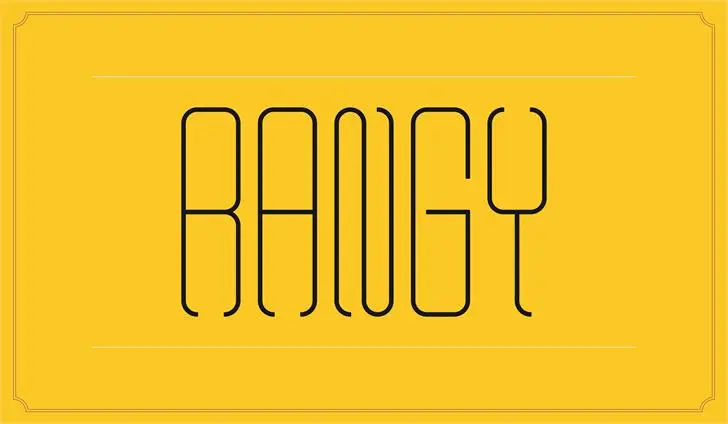
Rangy Font – Fonte Grátis
Rangy Font
A fonte Rangy é uma experimentada tipografia livre para uso comercial e pessoal projetada especificamente para títulos de revistas de moda e produtos cosméticos. Inspirada nos papéis clipados, esta tipografia foi desenvolvida seguindo as medidas da proporção dourada. Além disso, Rangy destaca-se por seu aspecto suave, fino e alongado. Este design criativo e funcional é perfeito para capturar a atenção do consumidor e dar um toque de elegância aos seus materiais. Ideal para qualquer aplicação onde você deseja criar um ar sofisticado e atemporal, seja em campanhas publicitárias ou em editoriais de moda. Seu designer experiente e talentoso, Hamilton, trouxe a Rangy ao mundo, oferecendo uma solução ideal para designers que buscam uma fonte única capaz de destacar suas criações. A fonte não só é versátil em tamanho e estilo, mas também respeita o seu uso tanto comercial quanto pessoal. Esta fonte Blackletter pode transformar a maneira como você apresenta o design gráfico, oferecendo um toque único que certamente deixará sua marca registrada mais distintiva. Engane-se se acreditar que Rangy é apenas uma fonte de moda; com seu desenho suave e alongado, ela pode ser usada em diversos contextos, desde logotipos até design de websites, garantindo um visual elegante e moderno sempre que necessário.